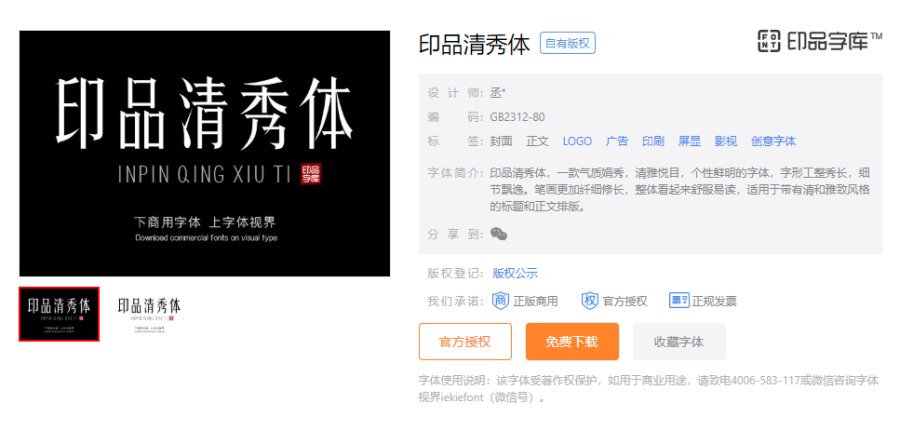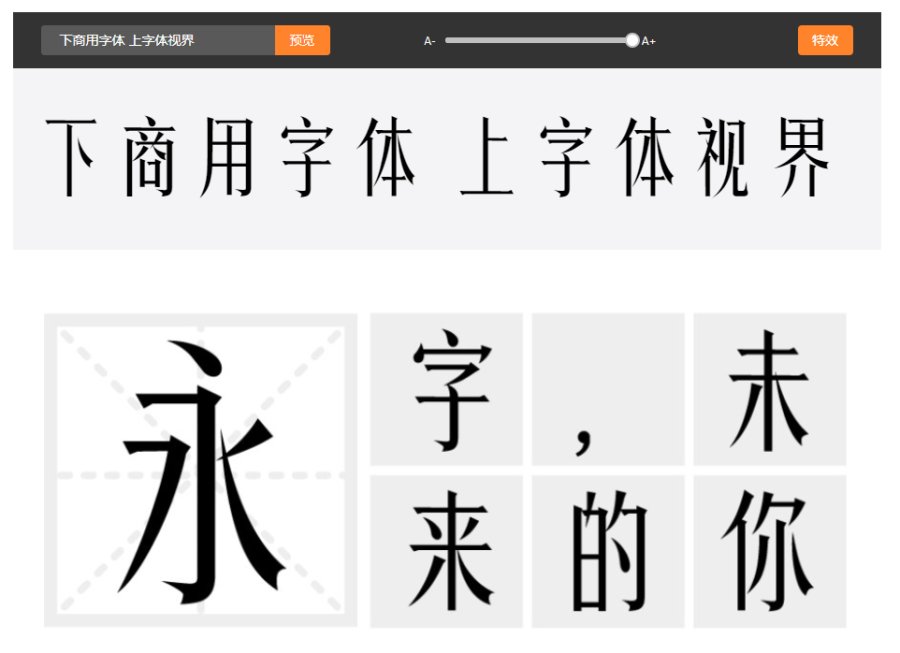
印品清秀体 | 新字下载_官方资讯
印品清秀体,是一款气质娟秀,
清雅悦目,个性鲜明字体。工整秀长,穿透的尖端。
笔画均匀,末端有装饰角,点、撇、捺、钩等笔画有穿透的尖端,
使字体更具有识别度。
对比与印品鸿蒙体,
印品清秀体字形工整秀长,细节飘逸。这款字简洁明快,
笔画更加纤细修长,整体看起来舒服易读,适用于带有清和雅致风格的标题和正文排版。